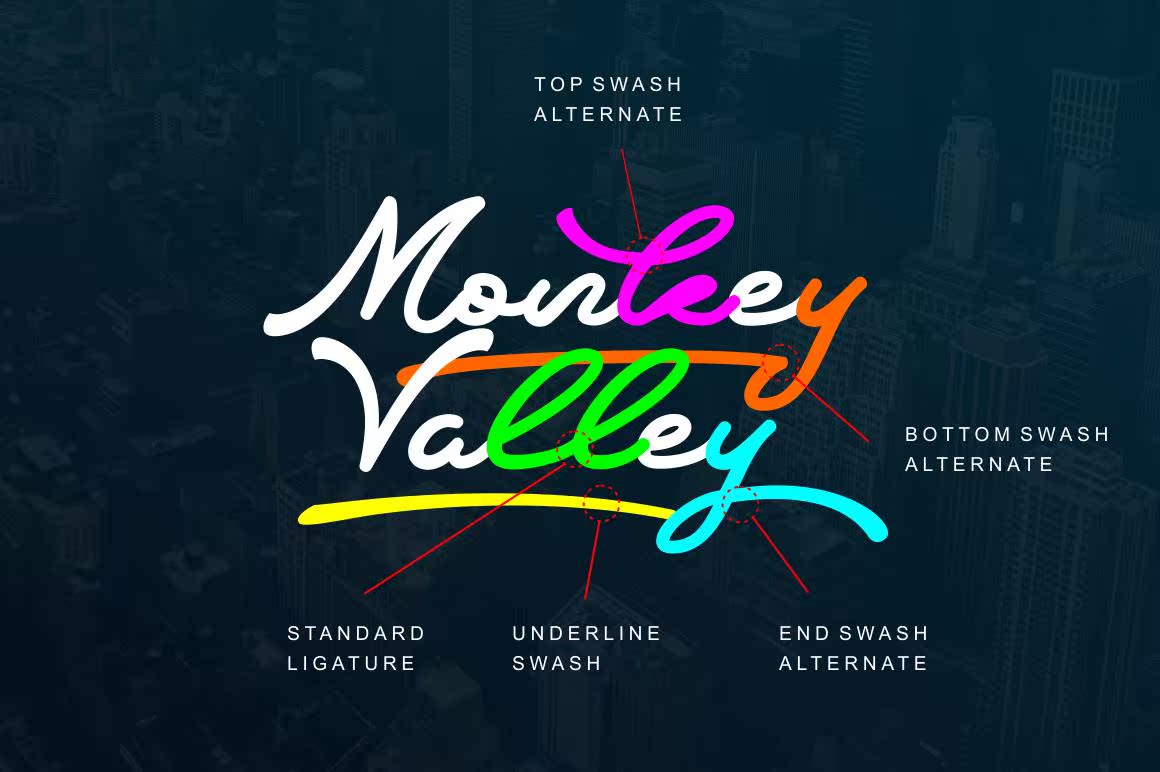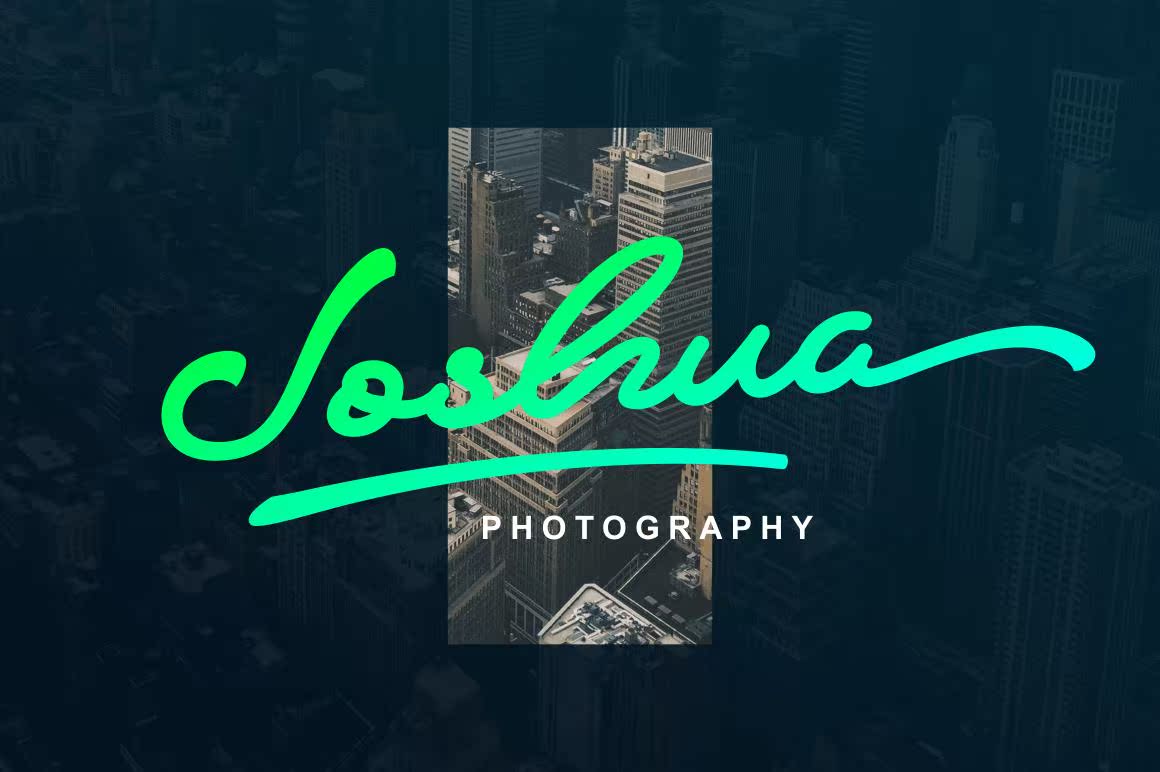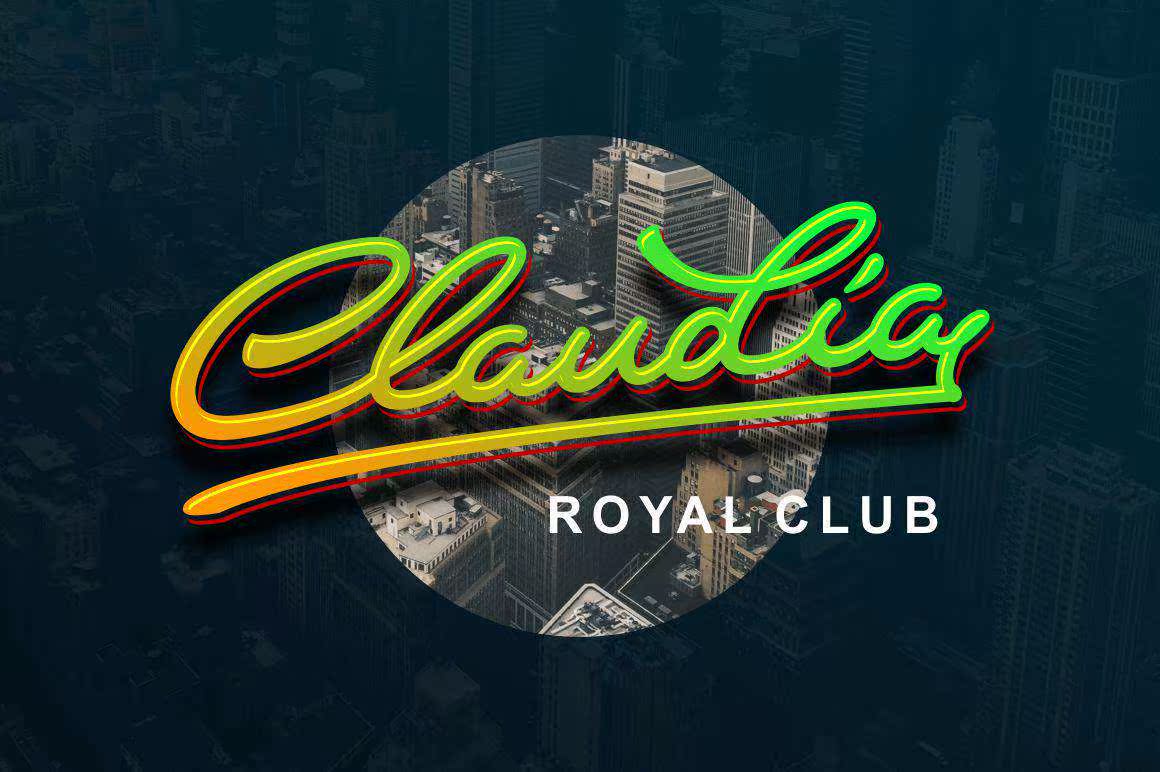
带有签名样式的Legant和ClassyScript。可称为“Crumble”,但该字体已被精心开发,以获得最佳的移动流。该字体将在以下方面完美呈现:徽标、制作一些引用、海报、婚礼宣传、,等。甚至对你的正文也能起作用。你可以使用OpenTypeFeatures检查Review for Better Lookatan。一个带有签名样式的Legant和ClassyScript。可以称为“Crumble”,但这个字体已经得到了充分的开发,以获得最佳的移动流。这个字体将在以下方面对一些人来说是完美的:徽标、制作一些引用、海报、婚礼宣传、,等。甚至可以用于正文。您可以使用OpenTypeFeatures来检查查看或查看文本